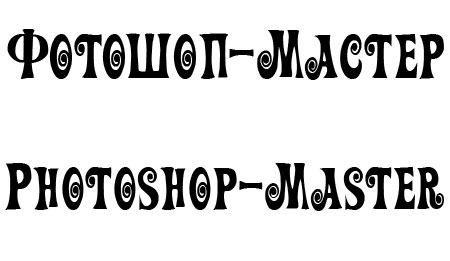
Дополнения Шрифты Татьяна Гапонова 1 апреля 2009 Шрифт - Auction Интересный шрифт для работы в Фотошоп. С поддержкой русского языка Скачать Шрифт - Auction
А в Word-e он без завитушек...